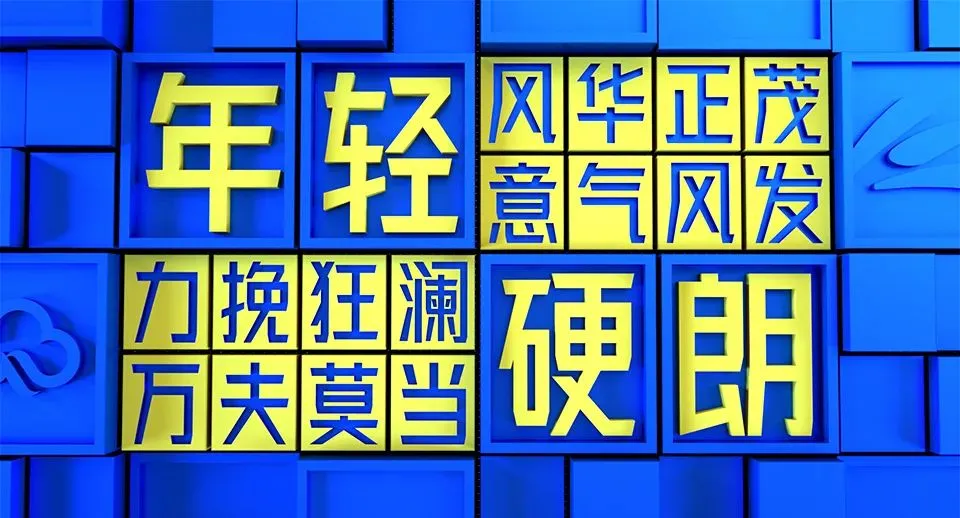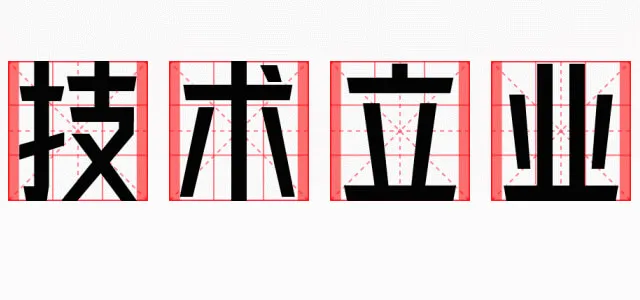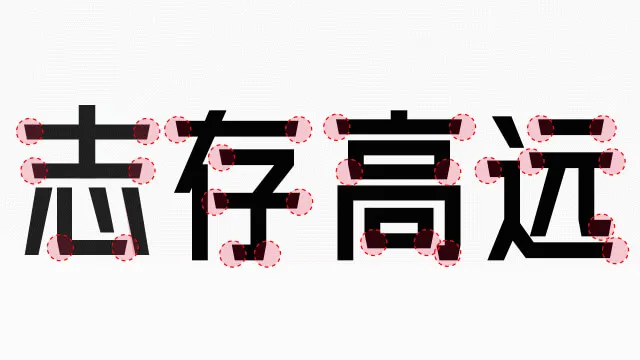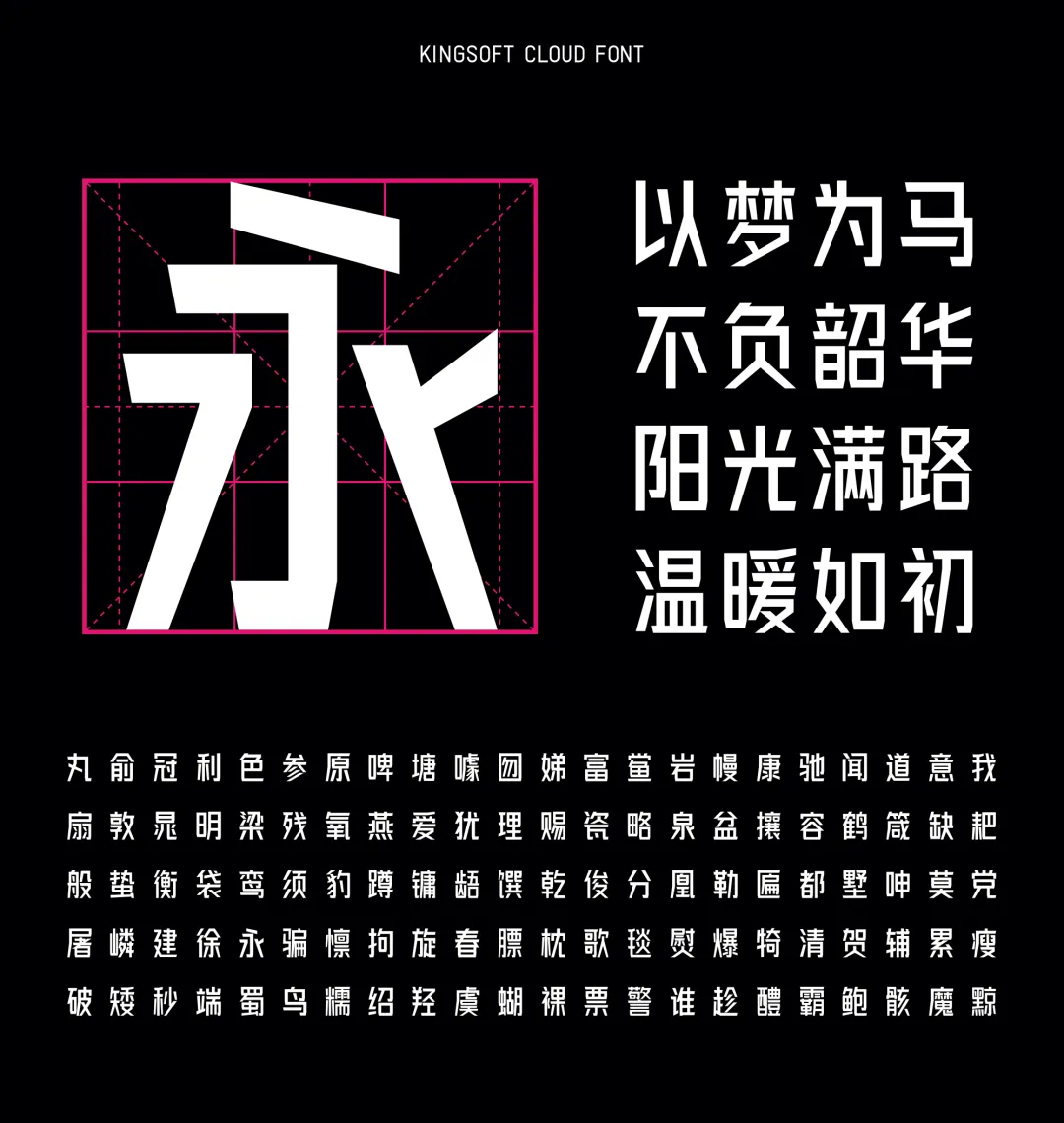
33年前,金山軟件因“字”而生,33年後,金山雲發佈首款原創字體庫,金山雲UED設計團隊,秉持著金山人“技術立業”的精神,歷時四年,逐點逐字,匠心設計。
“金山雲技術體”是一款無襯線體,提供一種標準版字重,文字參照GB2312簡體中文編碼字符標準。包含國標一級、二級字庫漢字6763個,外文及數字符號804個,總字符數7567個。
設計理念:字體在整體造型設計上,風格偏向年輕、硬朗、具有活力。
設計師:金山雲用戶體驗部的視覺設計同學們,歷時4年完成字庫,參與到字體制作的設計師(宋輝、李業鵬、劉雨凡、解磊、郭嘉琦、張立明、馮芷欣、王鵬飛、毛燕妮、閆佳妮、王思雨、張婧雨、劉淼)。
重新定義1:0.84的字寬比例,設計了整體、左右、上下等搭配方法。讓筆劃多的字與少的字,放在一起看盡量協調,減少視覺疏密感。
筆劃:為了打破常規黑體的生硬感,我們選擇了最複雜的設計方案,字體的筆劃設計根據整字權重劃分粗細進行搭配。
修飾:在筆劃的銜接和末端處,使用了12度的傾斜設計。![]()